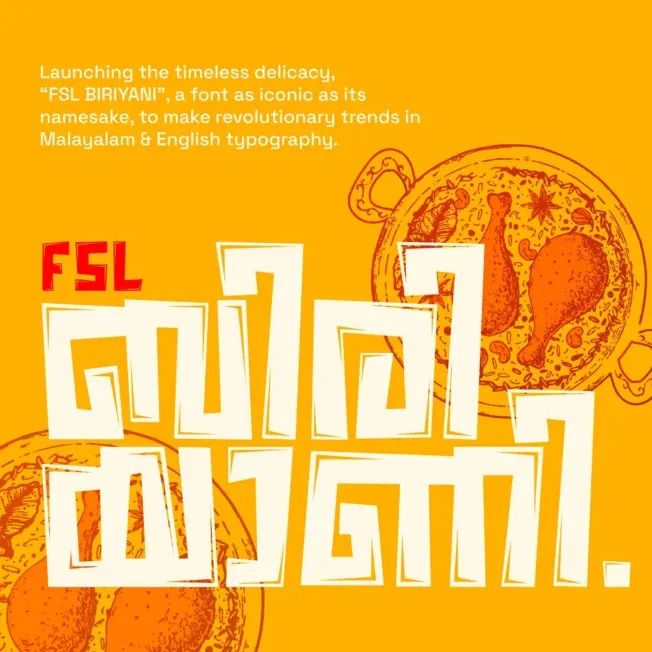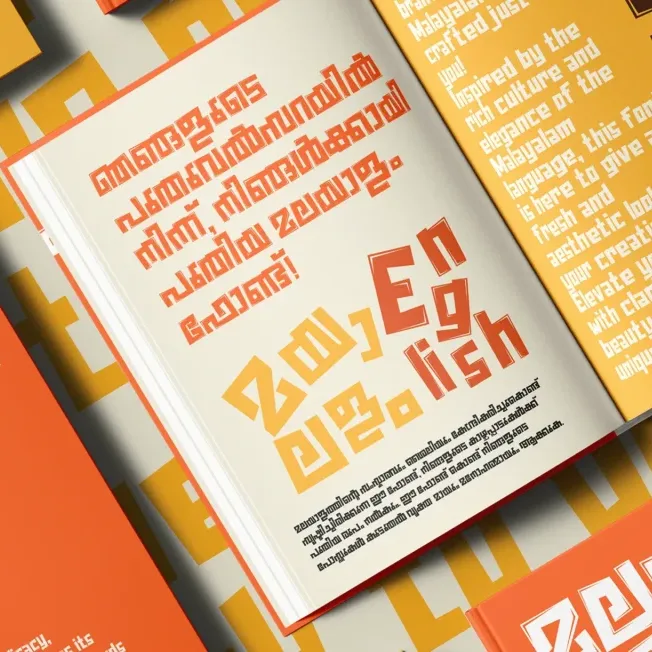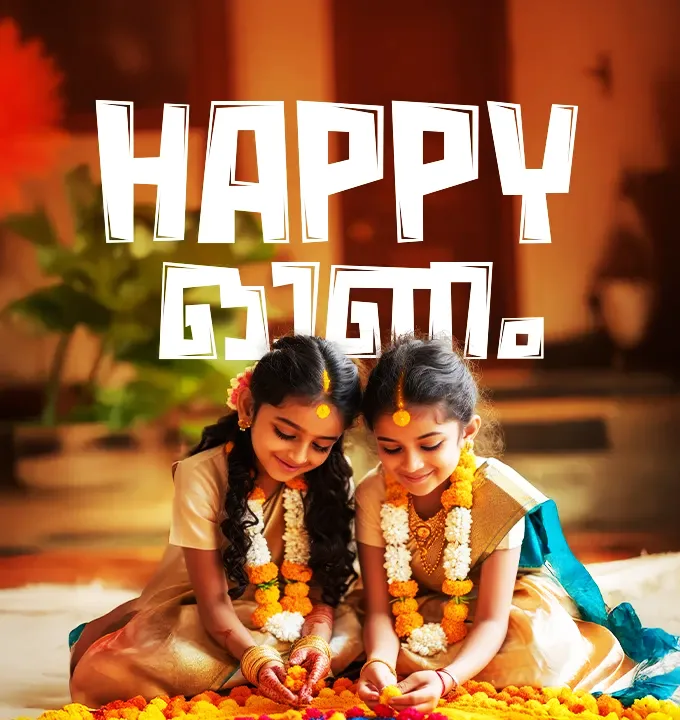
FSL-Biriyani | Unique Stylish Malayalam Display Font
ഡിസൈനുകളിൽ വേറിട്ടൊരു ശൈലി ആഗ്രഹിക്കുന്നവർക്കായി പുറത്തിറങ്ങിയ മനോഹരമായ ഒരു ഡിസ്പ്ലേ ഫോണ്ടാണ് FSL-Biriyani. അക്ഷരങ്ങളുടെ വ്യത്യസ്തമായ മോഡേൺ ലുക്ക് ഈ ഫോണ്ടിനെ മറ്റ് ഫോണ്ടുകളിൽ നിന്ന് വേറിട്ടു നിർത്തുന്നു. ബ്രാൻഡിംഗിനും സോഷ്യൽ മീഡിയ പോസ്റ്ററുകൾക്കും ഒരുപോലെ അനുയോജ്യമായ രീതിയിലാണ് Fontspell രൂപകല്പന ചെയ്തിരിക്കുന്നത്.
പ്രത്യേകതകൾ:
Unique Visual Appeal: അക്ഷരങ്ങളുടെ ജ്യാമിതീയമായ ശൈലി (Geometric style) ഏത് ഡിസൈനിനും ഒരു പ്രീമിയം ലുക്ക് നൽകുന്നു.
Versatile Display Font: ടൈറ്റിലുകൾക്കും പോസ്റ്ററുകൾക്കും ലോഗോകൾക്കും ഒരുപോലെ ഉപയോഗിക്കാൻ സാധിക്കുന്ന ഒരു ഡിസ്പ്ലേ ഫോണ്ടാണിത്.
Modern Design: പരമ്പരാഗത രീതിയിൽ നിന്ന് മാറി ചിന്തിക്കുന്ന ഡിസൈനർമാർക്ക് പരീക്ഷിക്കാവുന്ന ഒന്നാണ് ബിരിയാണി ഫോണ്ട്.
Wide Usage: ഫിലിം ടൈറ്റിലുകൾ, യുട്യൂബ് തമ്പ്നെയിലുകൾ, പരസ്യങ്ങൾ എന്നിവയിൽ ഈ ഫോണ്ട് ഇപ്പോൾ വ്യാപകമായി ഉപയോഗിക്കപ്പെടുന്നുണ്ട്.
നിങ്ങളുടെ ക്രിയേറ്റീവ് പ്രോജക്റ്റുകളിൽ വ്യത്യസ്തമായ ഒരു മലയാളം ലുക്ക് കൊണ്ടുവരാൻ FSL-Biriyani മികച്ചൊരു ചോയ്സ് ആണ് .